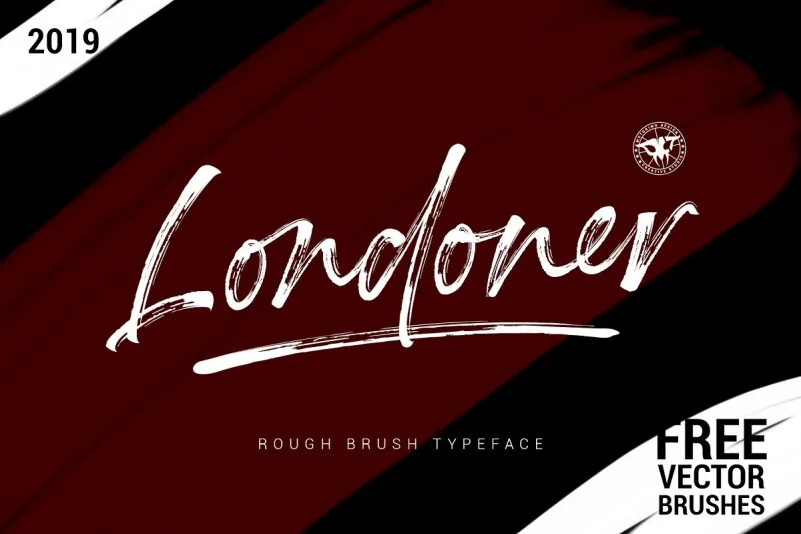
Londoner Brush Font – Download Grátis
Boa tarde! Seu interesse por fontes especiais está no lugar certo com a Londoner Brush Font. Esta elegante fonte à mão escrevendo foi criada com um pincel, trazendo uma energia forte e dinâmica aos seus textos. Motokiwo introduz a Londoner em seu catálogo de fontes, uma fonte feita à mão que mantém o texto leve mas vibrante, perfeitamente adaptado para logotipos ou qualquer aplicação onde você precisa de uma aparência única e contagiante. Com textura de pincel seco, a Londoner foi criada diretamente usando um marcador vetorial. Todo o processo é digitalizado, resultando em uma experiência de escrita à mão que transmite vida e entusiasmo. Além disso, todos os seus marcadores vetoriais também vêm com o seu próprio pincel na fonte bonus pack. A Londoner Brush Font é ideal para diversos usos, incluindo logotipos, marca de produtos ou até mesmo como um overlay textual para qualquer imagem de fundo. Tornar sua identidade visual mais única e vibrante nunca foi tão fácil quanto com esta fonte!